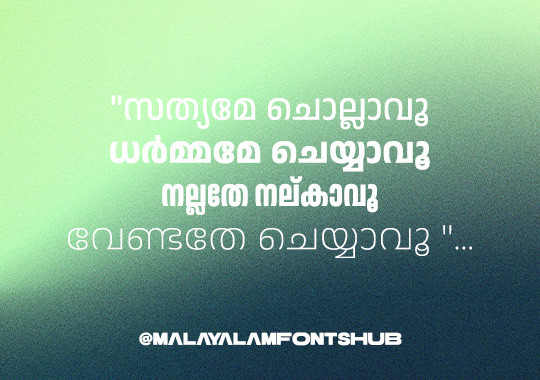
Anek | Modern Multi-Weight Sans-Serif Malayalam Font
2022-ൽ ഗൂഗിൾ ഫോണ്ട്സിലൂടെ പുറത്തിറങ്ങിയ Anek Malayalam, മലയാളം ഡിജിറ്റൽ ടൈപ്പോഗ്രാഫിയിൽ ഒരു വിപ്ലവം തന്നെ സൃഷ്ടിച്ച ഫോണ്ടാണ്. അക്ഷരങ്ങളുടെ ലളിതവും ആധുനികവുമായ രൂപകൽപ്പന (Modern Sans-serif design) ഏത് തരം ഡിസൈനുകൾക്കും ഒരു പ്രീമിയം ഫീൽ നൽകുന്നു. വൈവിധ്യമാർന്ന വാരിയന്റുകൾ അല്ലെങ്കിൽ അതിന്റെ കനം അനുസരിച്ചുള്ള വേർതിരിവ് ഉള്ള ഫോണ്ടുകൾ ഡൌൺലോഡ് ചെയ്യാൻ ലഭ്യമാണ് എന്നത് ഈ ഫോണ്ടിനെ ഡിസൈനർമാരുടെ ഇടയിൽ പ്രിയപ്പെട്ടതാക്കുന്നു.
പ്രത്യേകതകൾ:
9 Different Weights: Thin മുതൽ ExtraBold വരെയുള്ള 9 വ്യത്യസ്ത വെയ്റ്റുകളിൽ ഈ ഫോണ്ട് ലഭ്യമാണ്. ഇത് ഹെഡിംഗുകൾക്കും ബോഡി ടെക്സ്റ്റുകൾക്കും ഒരേപോലെ അനുയോജ്യമാണ്.
High Legibility: ചെറിയ വലിപ്പത്തിലുള്ള അക്ഷരങ്ങൾ പോലും വെബ്സൈറ്റുകളിലും മൊബൈൽ ആപ്പുകളിലും വളരെ വ്യക്തമായി വായിക്കാൻ സാധിക്കും.
Global Standard: ഏക് ടൈപ്പ് (Ek Type) ഡിസൈൻ ചെയ്ത ഈ ഫോണ്ട് അന്താരാഷ്ട്ര നിലവാരത്തിലുള്ള ടൈപ്പോഗ്രാഫി സൗകര്യങ്ങൾ ഉറപ്പാക്കുന്നു.
Perfect for UI/UX: വെബ് ഡിസൈനിംഗിനും ആപ്പ് ഡെവലപ്മെന്റിനും ഏറ്റവും അനുയോജ്യമായ ഒരു മലയാളം യൂണിക്കോഡ് ഫോണ്ടാണിത്.
നിങ്ങളുടെ വെബ്സൈറ്റുകൾക്കോ സോഷ്യൽ മീഡിയ പോസ്റ്ററുകൾക്കോ ഒരു മോഡേൺ ലുക്ക് നൽകാൻ Anek Malayalam മികച്ചൊരു തിരഞ്ഞെടുപ്പാണ്.